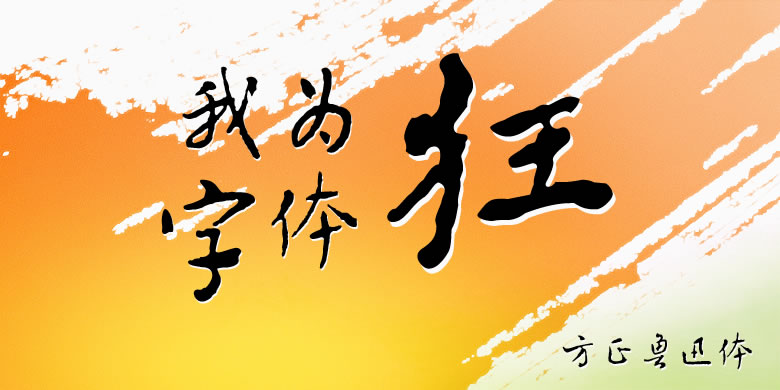
字体介绍 品牌:方正字库设计师:郭毓海发行时间:2016字库编码:大陆简体(GB2312-80)、简繁扩展(GBK)、大陆繁体(GB12345-90)分类:常规书写·毛笔 英文名称:FZLuXTFW.TTF “方正鲁迅体”集创于鲁迅书信与文稿。鲁迅字体清和古雅,萧散自如,极富人文气息和审美价值。见字如晤,通过鲁迅的字体,人们可以感受到一代伟人的精神风貌。鲁迅体字库为社会各界应用鲁迅字体、传播鲁迅精神提供了实用上的便利。鲁迅体字库的推出是对伟大的思想家、文学家鲁迅的长远纪念。 字体下载 官方下载